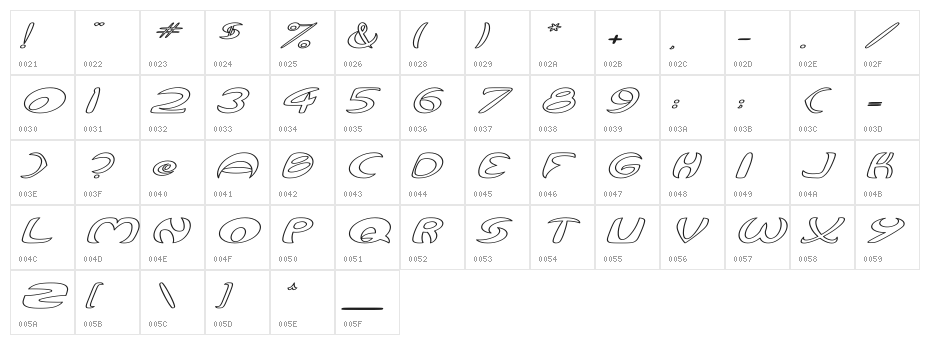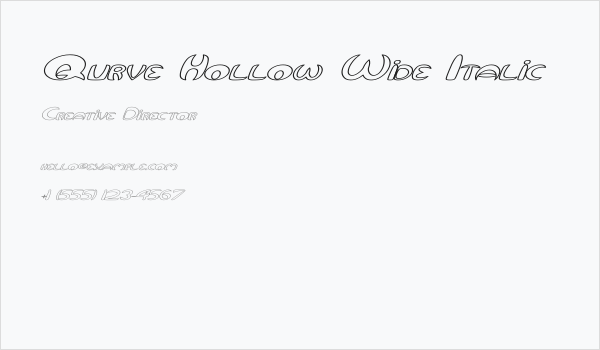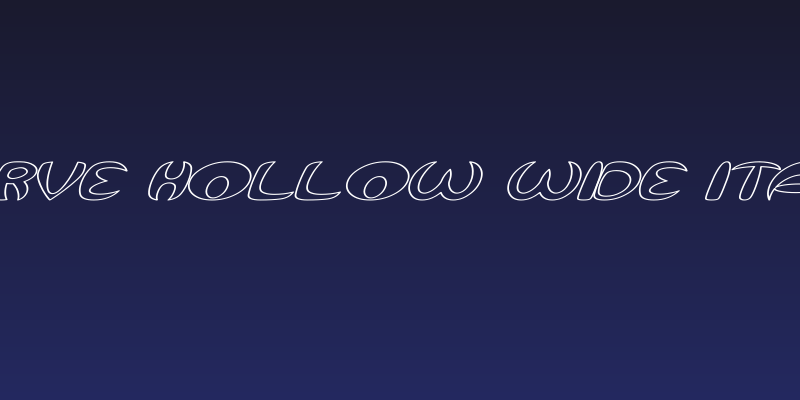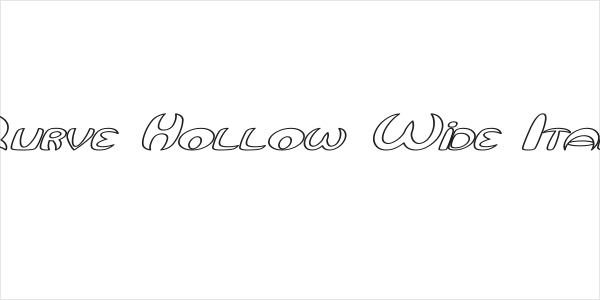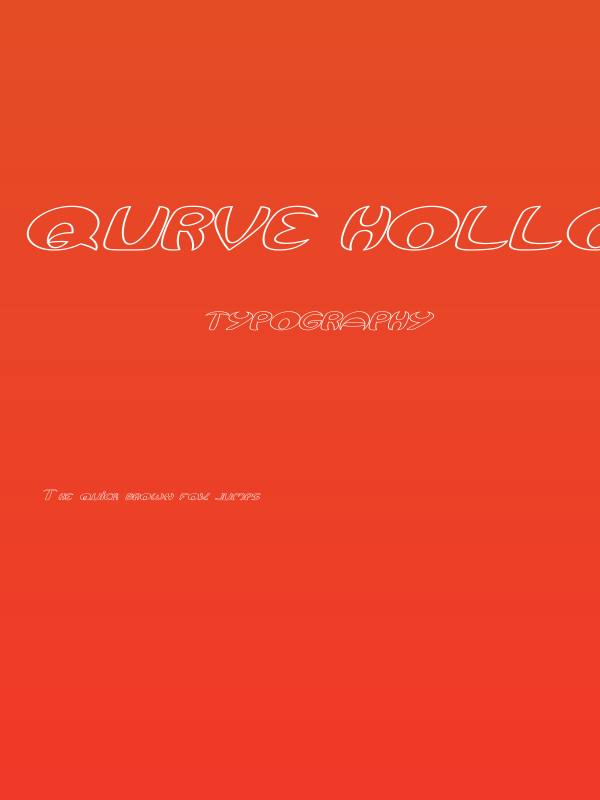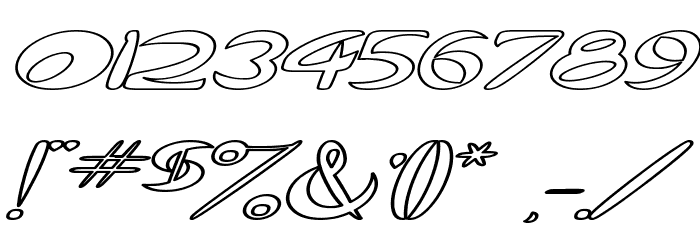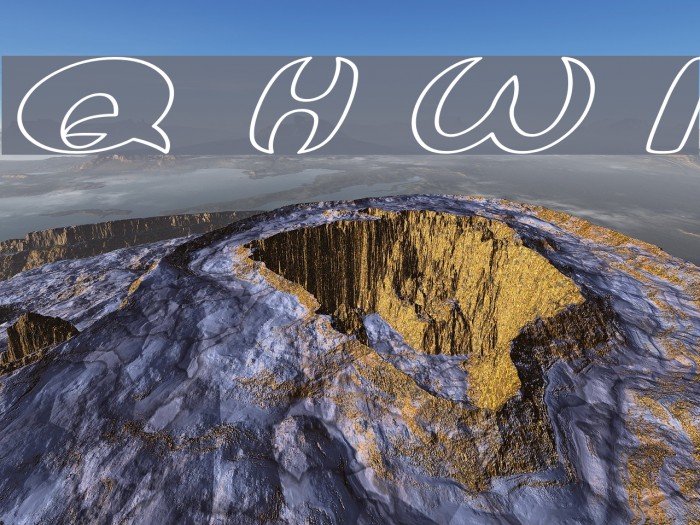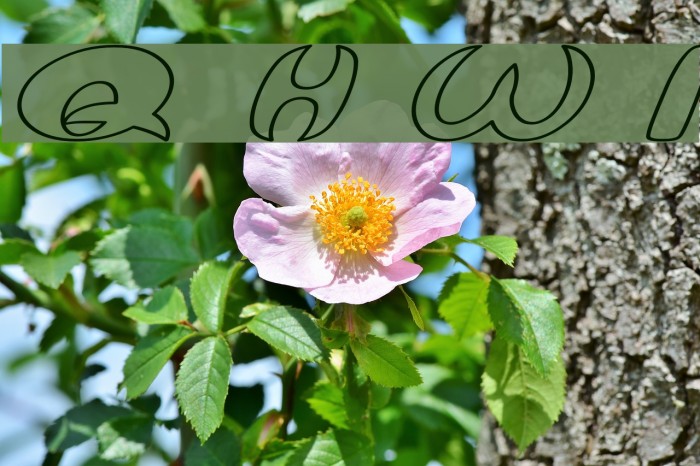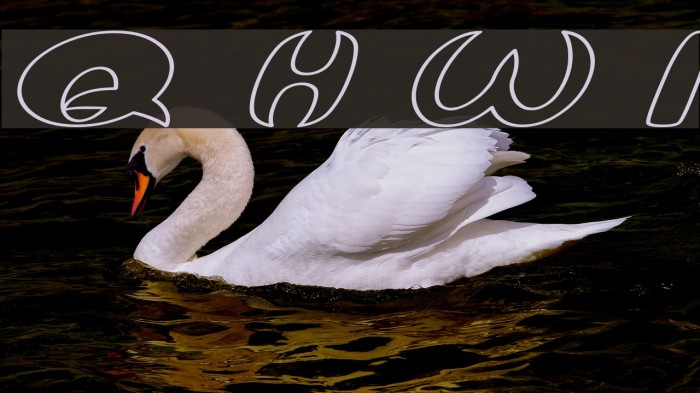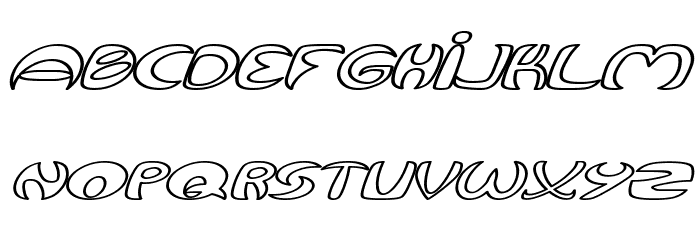
Qurve Hollow Wide Italic Font
✎ Outline
| Vorgeschlagene Projekte | Ideal for branding, advertising, posters, and headlines where a bold and modern look is desired. |